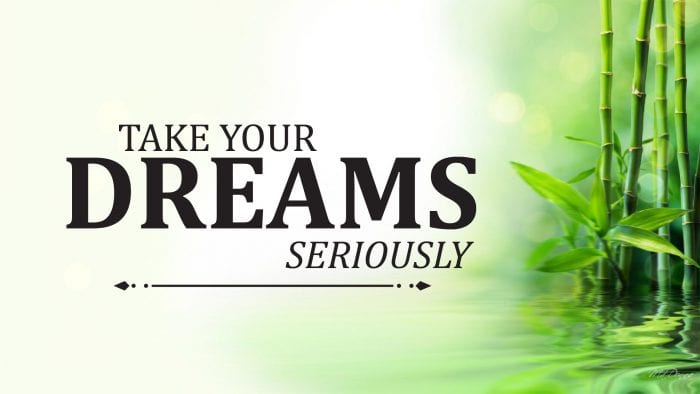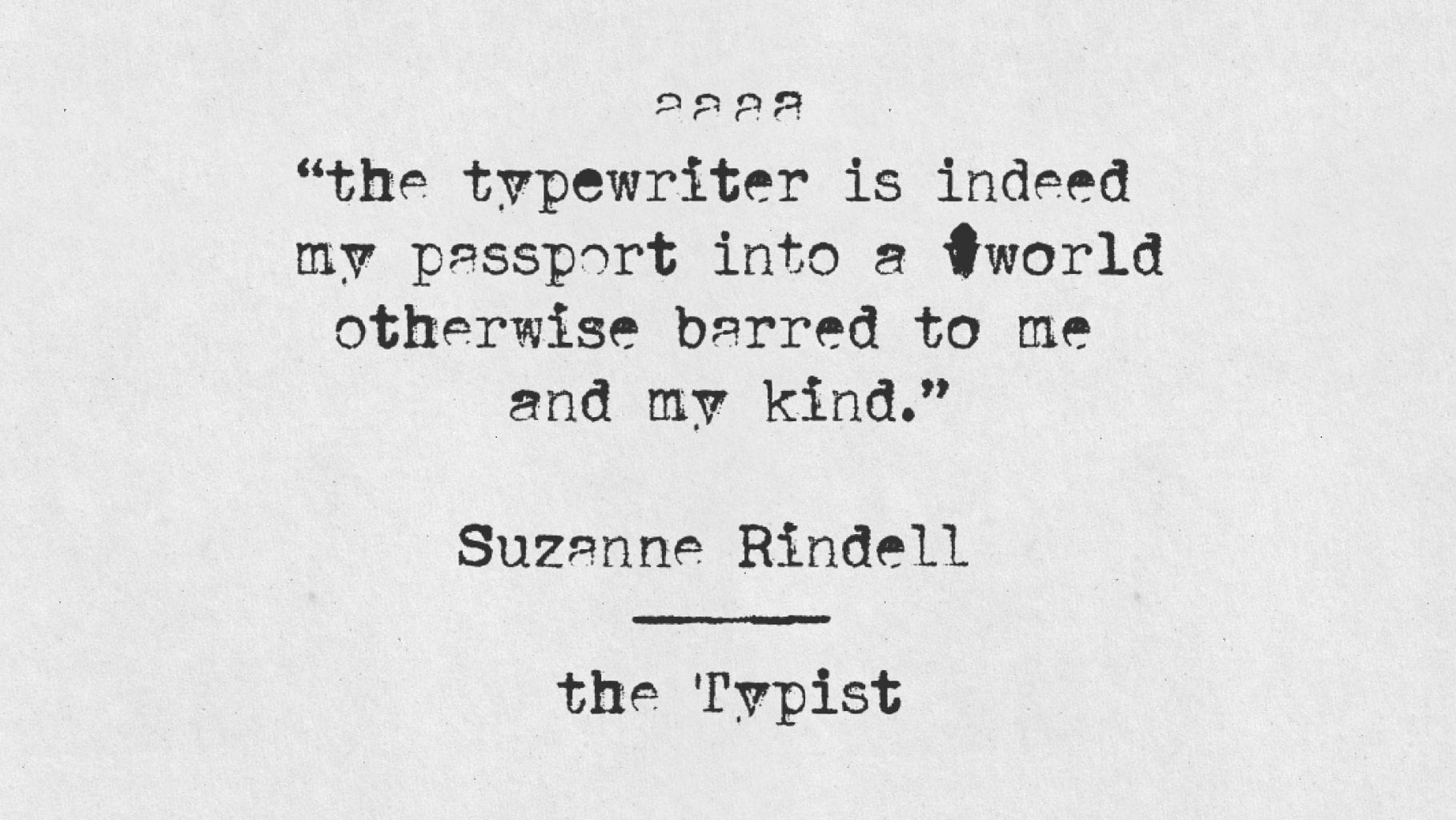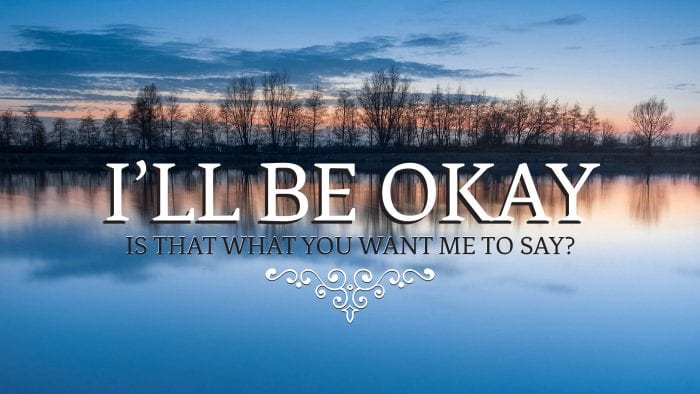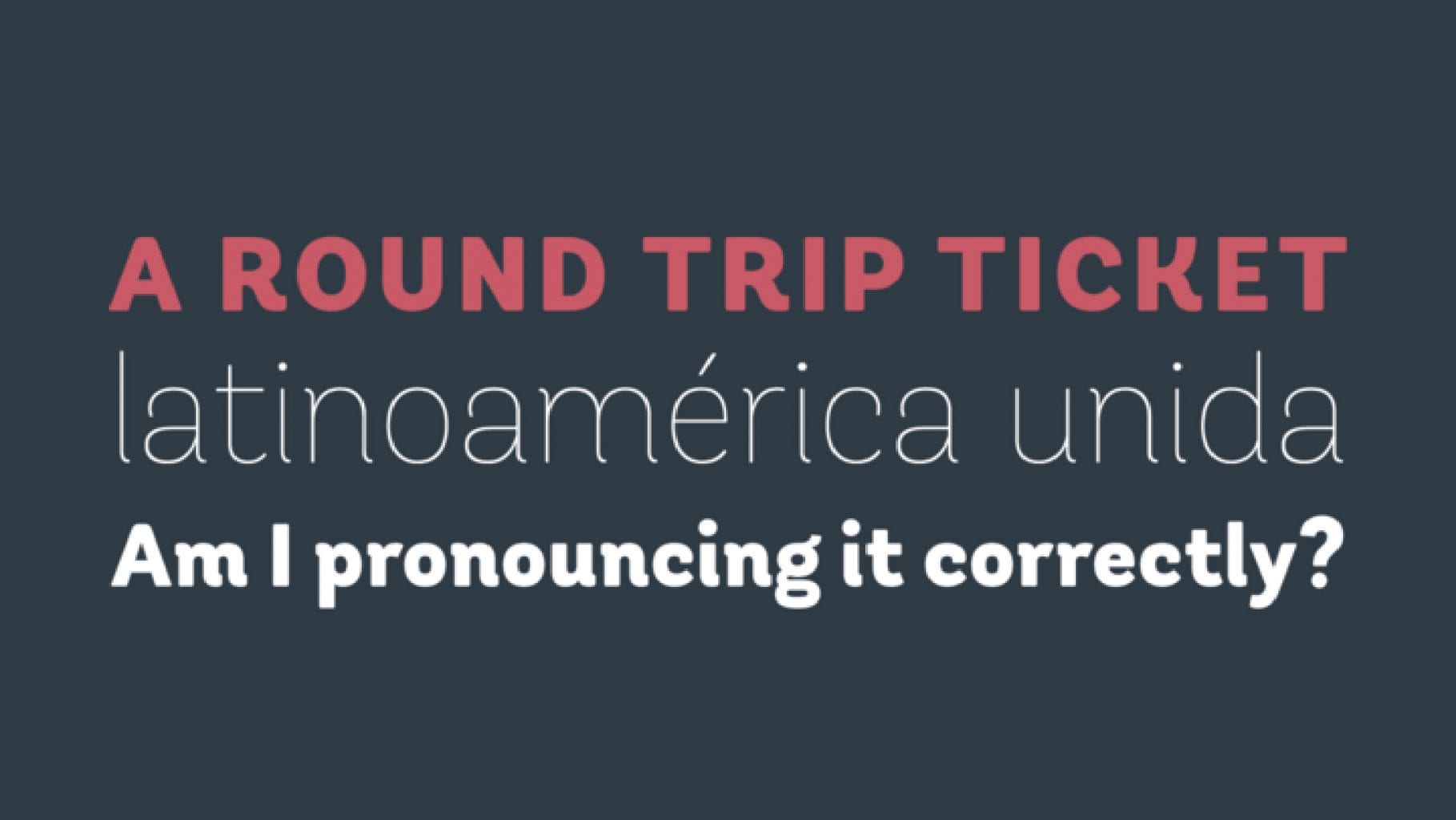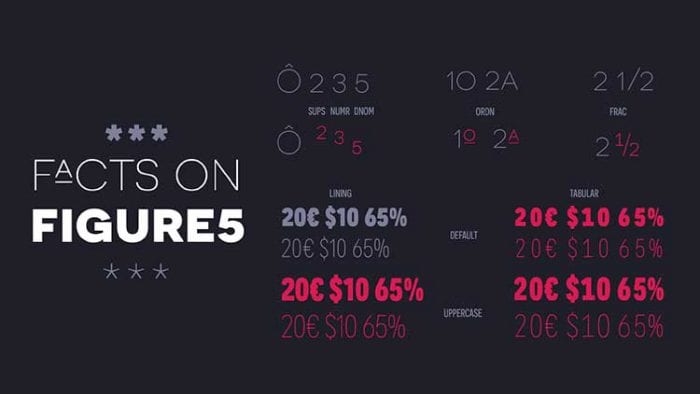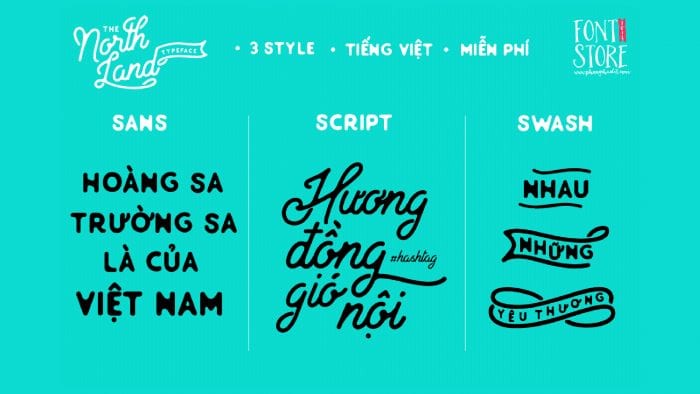
Trong bài viết hôm nay, Advertising Vietnam sẽ giới thiệu đến bạn một số font Việt hóa phổ biến ở phong cách serif và sans-serif, thường được sử dụng để thiết kế ấn phẩm bởi tính đơn giản, dễ vận dụng và quan trọng là không bị lỗi.Bởi trong thiết kế, ngoài hình ảnh thì font chữ cũng là một trong những yếu tố quan trọng thu hút sự chú ý của người xem. Đối với việc làm marketing trên các nền tảng trực tuyến cũng thế. Font chữ trên các thiết kế quảng cáo, poster...có tác động rất lớn đến nhận thức của khách hàng.
Font Việt hóa phong cách serif
Serif là kiểu chữ có chân, mang tính cổ điển. Người ta thường dùng nó cho những thương hiệu đậm chất cổ điển hoặc sang trọng. Bạn sẽ thường xuyên thấy phong cách serif xuất hiện trong thời trang và ngành in ấn.Những font Việt hóa mang phong cách serif tuy đơn giản nhưng chính sự đơn giản đó chính là điểm cộng thu hút sự chú ý của người xem. Một vài font serif Việt hóa chúng ta thường hay gặp trong các ấn phẩm báo chí, sách, thiết kế văn bản phải kể đến như:
- Font Cambria: thanh lịch duyên dáng với nét chân chữ rõ ràng. Nếu muốn thể hiện một đoạn văn bản nghiêm túc, trang trọng nhưng không muốn quá cứng nhắc với kiểu font Times News Romans thì Cambria là lựa chọn phù hợp nhất với bạn lúc này.
Font Việt hóa Cambria
- Font Traveling Typewriter: Ngay chính cái tên cũng đã thể hiện được “diện mạo” font chữ này. Nếu bạn là người bị thu hút bởi những nét chữ đánh máy ngày xưa, đơn điệu nhưng có chất riêng thì đây chính là font chữ bạn đang cần.
Font Việt hóa Typewriter
- Font Fénix: Cha đẻ của font chữ này, Fernando Díaz cho biết ông lấy cảm hứng từ chữ calligraphy (một dạng chữ viết tay từ bút lông và mực). Chính vì vậy mà chúng ta có thể thấy được sự kết hợp hài hòa giữa những đường gạch chân mạnh mẽ và các đường bo tròn mềm mại. Đối với những đoạn văn bản dài, bạn có thể sử dụng font Việt hóa này để tạo cảm giác hứng thú cho người đọc.
Font Việt hóa Fénix
- Font Hapna được giới thiệu lần đầu tiên vào tháng 1 năm 2013, được lấy cảm hứng từ bóng chày và những ấn phẩm từ năm 1950. Bộ font bao gồm 6 kiểu từ Light cho đến Black, đã được việt hóa trọn bộ, kerning và opentype hoàn chỉnh.
Font Việt hóa Hapna
Font Việt hóa phong cách Sans-Serif
Sans-Serif, đúng như tên gọi của mình, kiểu font này không có gạch chân (serif) trong cấu trúc chữ. Sans-Serif được tạo ra sau Serif với những đường nét mới mẻ hơn. Nó thường được dùng cho những thương hiệu công nghệ bởi tính dứt khoát, rõ ràng. Bạn sẽ dễ dàng nhận thấy điều này khi nhìn vào các ứng dụng, trang web hay các nền tảng kỹ thuật số. Bởi điểm cộng lớn nhất của kiểu font này là rất dễ đọc trên giao diện điện thoại.Dưới đây là 1 số font sans-serif Việt hóa phổ biến trong các thiết kế:
- Font Uni Sans: Font chữ dùng được hầu hết trong tất cả các thiết kế: trang web, đồ họa, thời trang, poster, logo…Đặc biệt, nếu dùng font chữ này để thiết kế tựa đề thì chắc chắn bài viết của bạn sẽ tạo ấn tượng về mặt thẩm mỹ ngay.
Font Việt hóa Uni Sans
- Font Andes Rounded được đánh giá là sản phẩm hòa trộn giữa các trường phái typography. Font chữ này phù hợp với logo, tạp chí, sách báo…
Font Việt hóa Andes Rounded
- Font Novecento được sử dụng chủ yếu cho tiêu đề, thiết kế thương hiệu hoặc câu trích dẫn (quote). Các kiểu chữ mảnh của font này làm cho thiết kế trông hiện đại và kiểu chữ in đậm thì lại mang đến cảm giác cổ điển hơn.
Font Việt hóa Novecento
- Font Montserrat với thiết kế độc đáo được lấy cảm hứng từ những bảng chỉ dẫn của vùng Bueno Aires, thường được dùng nhiều trong việc thiết kế tiêu đề dạng chữ to. Do không có kiểu Italic nên font chữ này không phù hợp với những đoạn văn bản dài. Font chữ này đã được tinh chỉnh ở cả giao diện máy tính và điện thoại.
Font Việt hóa Montserrat
- Font North Land: Đây là bộ font kết hợp từ typography, lettering handmade, swash cùng phong cách không chân gạch vừa được ra mắt vài tháng trở lại đây. Là kết quả của tổ hợp tinh tế, đơn giản, vừa hiện đại vừa cổ điển nên North Land nhanh chóng ghi điểm với người dùng. Bạn có thể dùng font này để làm typography, poster hoặc các dạng thiệp mời.
Font Việt hóa North Land
Bên trên là 9 font Việt hóa đơn giản, dễ áp dụng cho nhiều kiểu thiết kế. Tuy nhiên để sản phẩm của mình trông ấn tượng và đặc biệt hơn thì người dùng phải linh hoạt trong cách sử dụng. Chẳng hạn như việc pha trộn các kiểu font lại với nhau sao cho hài hòa, cân đối.